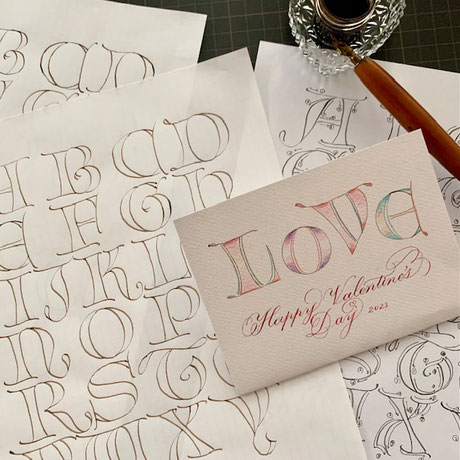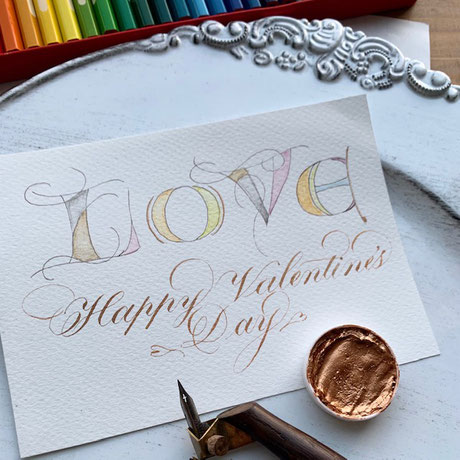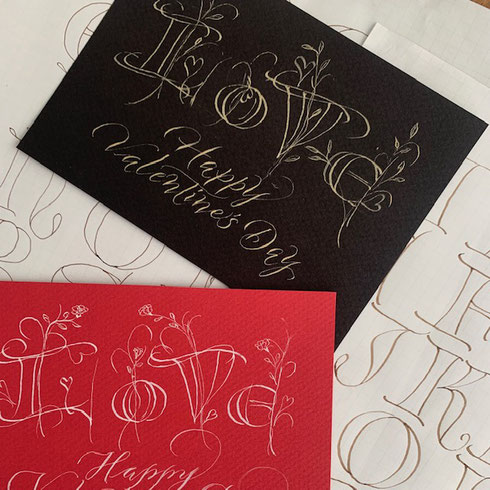
モダンヴァーサル体で作るヴァレンタインズデイカードです。
LOVEに使われた書体はロンバルディック体といい、10世紀くらいに今のイタリアのロンバルディア地方で書かれた文字です。
この文字は廃れてしまうのですが、中世に入った後も写本を彩る文字飾りとして使われ続けました。
今回は、伝統的な技法ではなくモダンデザインでヴァレンタインカードにあしらってみます。
上の作品は文字から春の花が伸びる様子を描いたものです。
他にも様々なデザインが考えられます。
上級者の方はまずはヴァーサル体としてのロンバルディック体を書く練習からはじめ、自分らしいモダンデザインの制作に入ってください。
初心者の方、中級者の方は、私の文字をトレースしてLOVEにモダンな彩色を施してくださるようにテキストを準備いたしました。